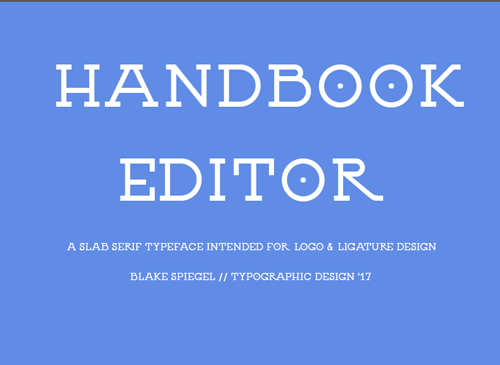
Handbook Editor Typeface – Download Grátis
A Befonts apresenta ao mercado a nova slab serif Handbook Editor Typeface, desenvolvida por Blake Spiegel para uma nova geração de design gráfico. Uma das características mais interessantes desta fonte é sua expressividade e força moderna. Seus traços soldados dão-lhe um aspecto robusto que se destaca em qualquer projeto. A Handbook Editor é perfeitamente adaptada tanto para logos quanto para cartões de visita, layouts de revistas, convites ou até mesmo como elementos de arte em grandes proporções. Ideal para aqueles que buscam um tipo forte e moderno, essa fonte tem a capacidade de transformar qualquer projeto no qual ela seja usada. Será sua escolha o diferencial para seu próximo trabalho!